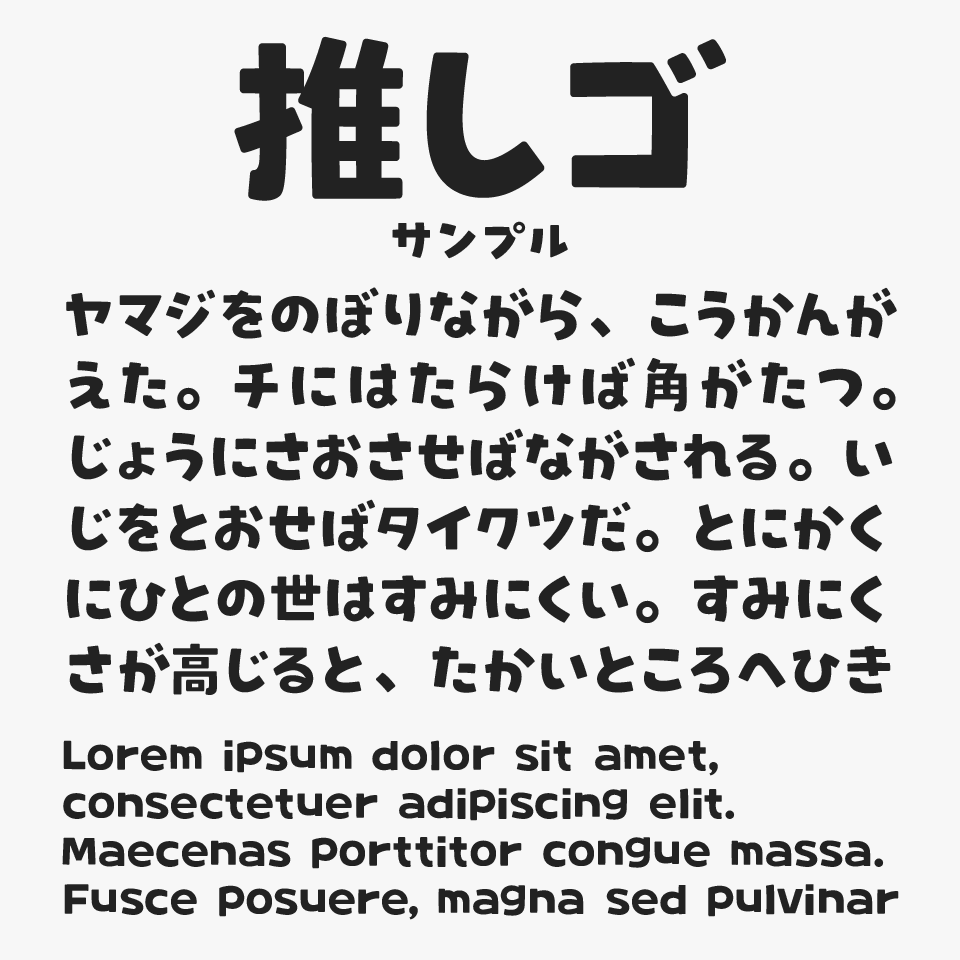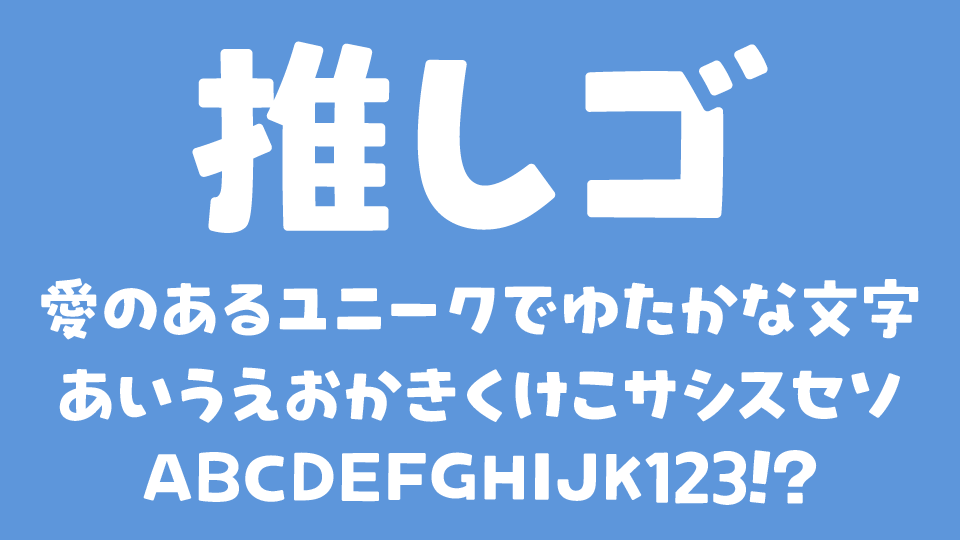
推しゴフォントは、推し活グッズ制作を目的に作られたフォントで太さもあり、遠くからの見えやすさにこだわって作られたゴシック体フォントです。
ライブやコンサートなどに推し活グッズを持ち込んだ際に、遠くにいる推しにも見えるように・目立つように考えられているため、太さとインパクがあるデザインです。かつ、やららかくポップな印象に見えるように角丸になって、少し崩しているのが可愛い印象を感じます。
推し活うちわ制作を目的としてフォントなので、うちわで使えるアイコン32種類も使うことができるのも嬉しいポイントです!
推しゴのような“推し活”系で人気のあるフォントと比較してみると、推しゴは特に手作り感のあるやわらかな雰囲気が魅力です。(比較フォントは、トガリテ、にくまる、ビルと谷間と高架下、チェックアンド、あおさぎ、りいクッキー、チェックポイント、ニコモジ+もとても可愛らしいフォントなので、あわせてチェックしてみてください。)
収録文字は、ひらがな・カタカナ・英数字・記号の他、一部ファンサ文言に対応した漢字121字が収録されています。